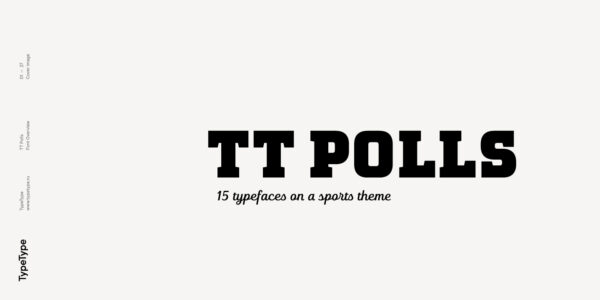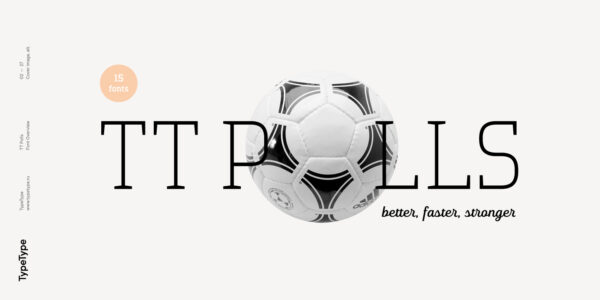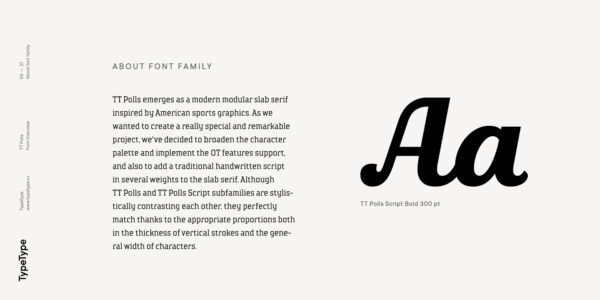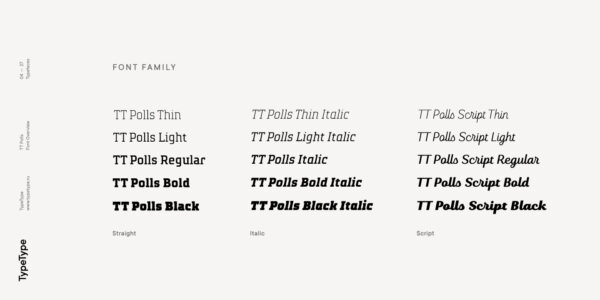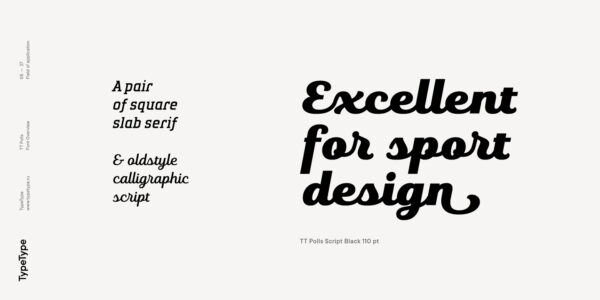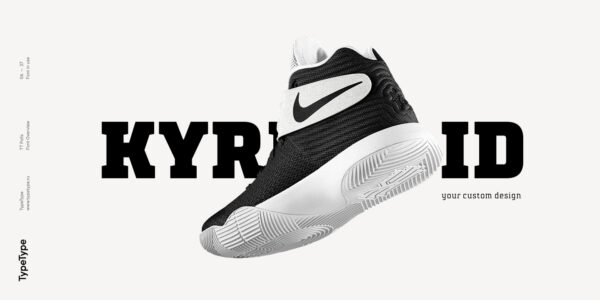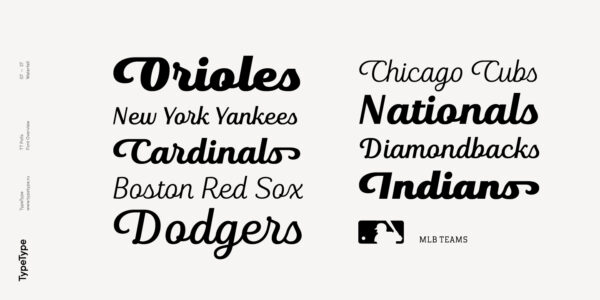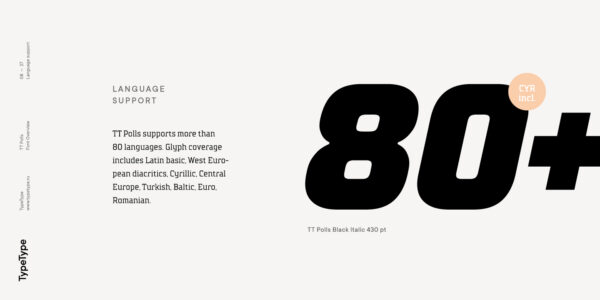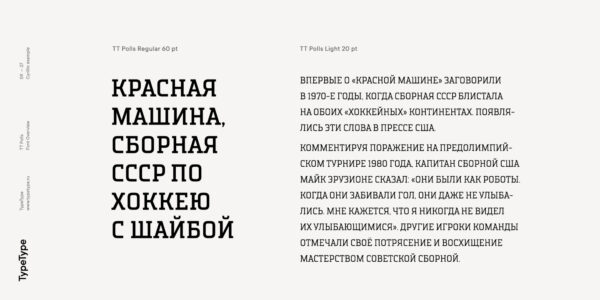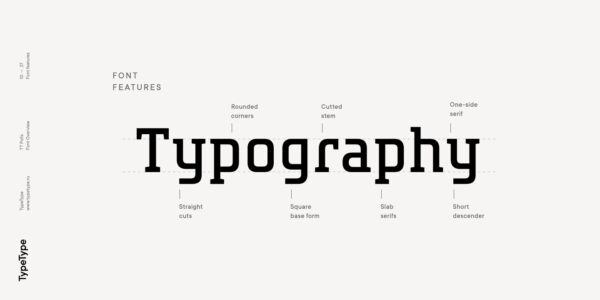
TT Polls
TT Polls — ТТ Поллс
Произносится «ТТ Поллс». «Polls» — производное слово от poll, в переводе с английского языка «голосование», отсылка к голосованиям в спортивных соревнованиях. Буквы «TT» являются аббревиатурой названия компании.
TT Polls — гарнитура, вдохновлённая спортивной американской графикой. Состоит из модульного брускового шрифта и традиционного скрипта.
TT Polls
Cовременный модульный брусковый шрифт
Так как мы хотели сделать действительно особенный и запоминающийся проект, мы решили расширить палитру знаков и внедрить поддержку ОТ фич, а также добавить к брусковому шрифту традиционный рукописный скрипт в нескольких весах. Несмотря на то, что подсемейства TT Polls и TT Polls Script контрастируют между собой по стилистике, однако благодаря соответствию их пропорции они превосходно сочетаются между собой.
TT Polls выполненный по мотивам спортивной американской графики, но отлично подходит и для казуального дизайна
Подсемейство TT Polls состоит из 5 весов и 5 италиков
Идеальные шрифтовые пары с TT Polls
О гарнитуре TT Polls
Поддержка языков 160+
Шрифтовое семейство TT Polls берет свое начало как современный модульный брусковый шрифт, выполненный по мотивам спортивной американской графики. Так как мы хотели сделать действительно особенный и запоминающийся проект, мы решили расширить палитру знаков и внедрить поддержку ОТ фич, а также добавить к брусковому шрифту традиционный рукописный скрипт в нескольких весах.
Несмотря на то, что подсемейства TT Polls и TT Polls Script контрастируют между собой по стилистике, однако благодаря соответствию их пропорции, как в толщинах вертикальных штрихов, так и в общей ширине знаков, они превосходно сочетаются между собой.
Подсемейство TT Polls состоит из 5 весов и 5 италиков. Мы добавили в него сет лигатур и широкую поддержку OpenType features: calt, salt, liga, case, frac, sinf, sups, dnom, numr, tnum. А благодаря использованию стилистических альтернатив можно существенно изменить характер шрифта, сделав его более технологичным.
Хоть при создании шрифтового семейства TT Polls мы и держали в голове его использование в дизайне на спортивную тематику, будь то надписи на майках бейсболистов или цифры на бортах болидов, надо отметить что финальная версия TT Polls отлично подходит и для более казуального дизайна и сфер применения.
TT Polls Script
salt | Stylistic Alternates
agly
liga | Standard Ligatures
ffi fj
case | Case Sensitive Forms
({[H]})
dlig | Discretionary Ligatures
st sp